워드마크를 통한 리브랜딩 성공 사례
기업 혹은 브랜드가 빠르게 성장하게 되면 이전의 아이덴티티를 수정하거나 문제점들을 개선해야 할 경우가 종종 생기곤 합니다. 브랜드 가치를 재정립하고, 새로운 시각적 아이덴티티를 개발하는 과정을 바로 리브랜딩(Rebranding)이라고 합니다. 큰 규모의 기업이나 브랜드의 리브랜딩은 매우 큰 비용이 발생하고, 프로젝트의 방향성이 잘못될 경우 기존 브랜드의 팬층이 혼란을 겪거나 거부할 수도 있기 때문에 매우 신중히 진행되어야 하는 작업이기도 합니다.
오늘은 기업과 브랜드 아이덴티티에 대한 의견과 리뷰를 공유하는 플랫폼인 BrandNew에서 좋은 평가를 받았던 케이스 12개를 통해 최근 워드마크 트렌드를 세 가지를 소개하려고 합니다.
1. 세리프의 귀환
지난 몇 년간 수많은 기업과 브랜드들이 세리프 서체에서 산세리프 서체로 로고를 수정하는 것이 일종의 관례로 자리 잡았는데요, 특히 이런 리브랜딩은 유독 럭셔리 패션 브랜드에서 많이 볼 수 있었죠. 하지만 기존 브랜드가 갖고 있던 브랜드 고유의 개성을 버리고 모던함만 추구한다는 점에서 해당 브랜드의 팬층에게 강한 반발을 일으키기도 했습니다.
최근 리브랜딩 트렌드를 보면 이런 트렌드를 깨고, 오히려 브랜드의 특징을 살릴 수 있는 독특한 세리프 서체를 이용하여 해당 브랜드만의 독특한 아이덴티티를 구축하는 사례들을 볼 수 있습니다.
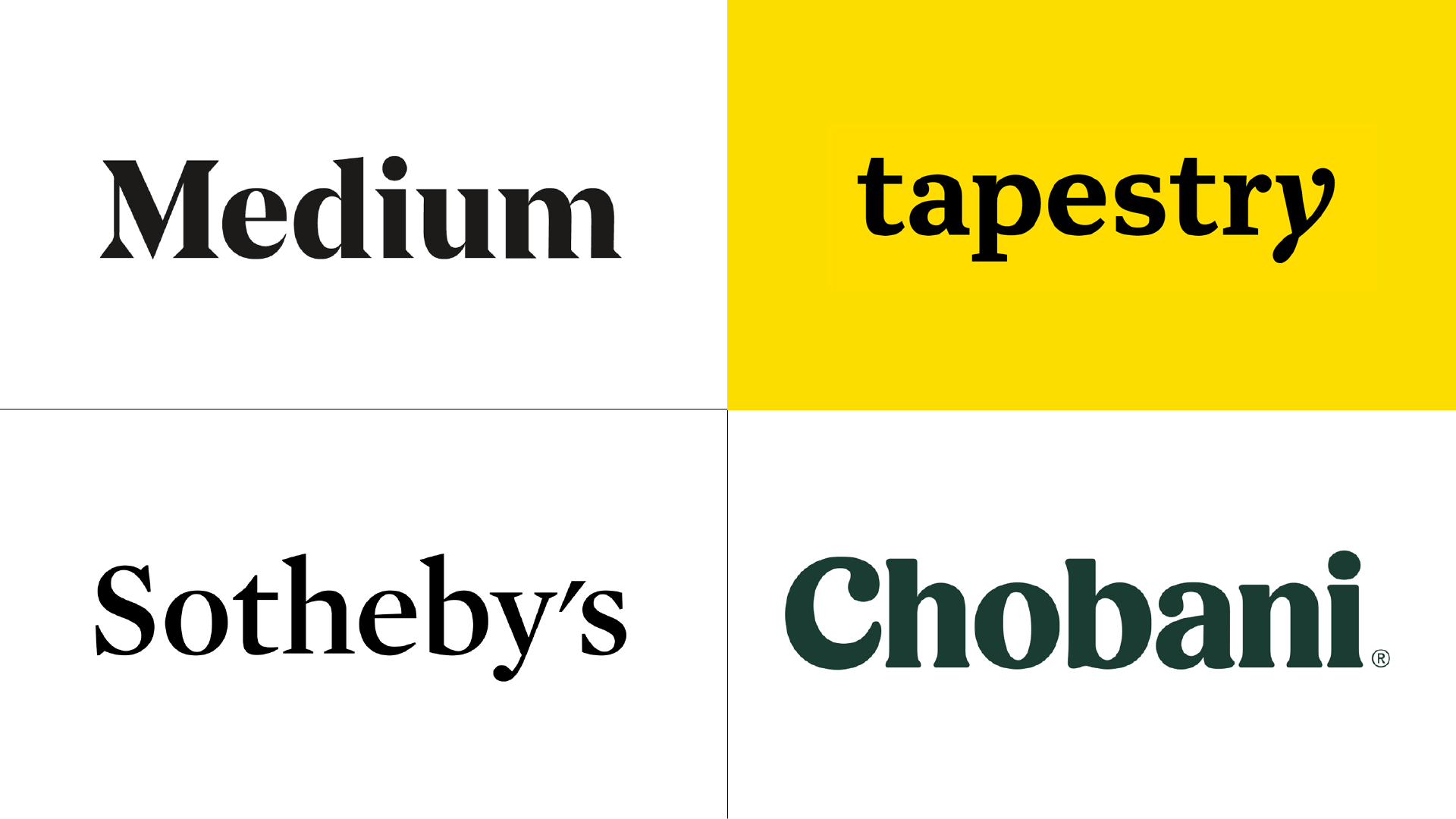
1) Medium
디자인 에이전시 Manual과 인하우스 협업
2012년에 서비스를 시작한 Medium은 미국판 Brunch라고도 불리는 대표적인 온라인 출판 플랫폼입니다. 서비스 초기에 여타 온라인 플랫폼들과 같이 모던한 산세리프체를 사용했던 Medium의 이전 아이덴티티는 다소 밋밋한 인상을 가지고 있었지만, 단단하고 개성 있는 세리프체를 활용한 리브랜딩을 통해 다른 서비스들과 비교하여 시각적으로 돋보이고 개성있다는 호평을 받았습니다
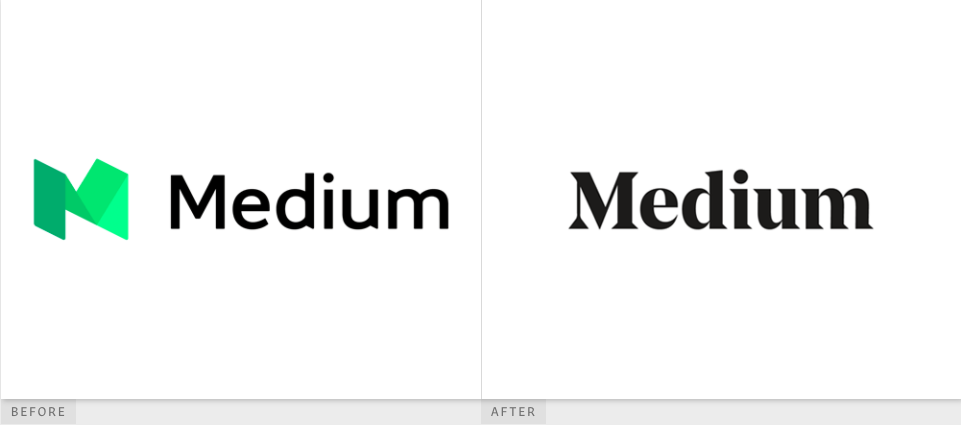
2) Tapestry
뉴욕 디자인 에이전시 Carbon Smolan Agency에서 제작
Tapestry는 Coach의 모회사로 Coach의 이름에 너무 의존하지 않기 위해 Coach Inc에서 수정된 이름입니다. Coach는 패션 브랜드 중에서 아직까지 세리프 폰트를 유지하고 있는 브랜드 중 하나인데요, 이번 Tapestry 리브랜딩에서도 공 모양의 세리프가 인상적인 서체를 사용하여 단단하면서도 부드러운 이미지의 워드마크를 제작하였습니다.
3) Sotheby’s
디자인 에이전시 Pentagram제작
Sotheby’s(소더비)는 1744년 영국, 런던에서 설립되어 고가 미술품을 취급하는 경매회사입니다. 산세리프 체인 Gill Sans체를 바탕으로 한 기존의 워드마크는 고가의 미술품을 취급하는 회사의 이미지에 비해 너무 모던하고, 신중하지 못하다는 느낌이 있었습니다.
이런 문제점을 개선하기 위해 펜타그램 뉴욕 파트너 Miller와 그의 팀은 세리프 서체인 Mercury체를 활용하여 300년이 넘는 Sotheby’s의 유산을 계승할 수 있는 아이덴티티를 선보였습니다.
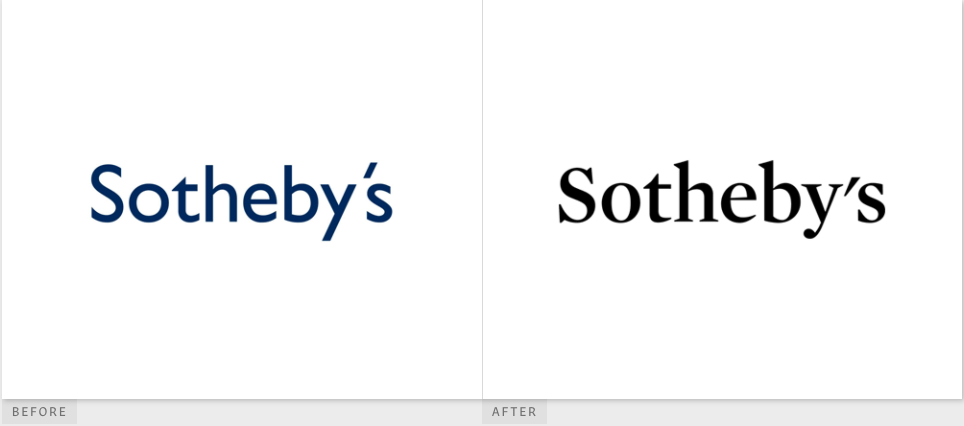
4) Chobani
인하우스 제작
2007년에 한 터키 이민자가 뉴욕의 그릭 요거트 공장을 사서 설립한 Chobani는 이제 미국에서 가장 잘 팔리는 요거트 브랜드입니다. 식품 브랜드로서는 다소 딱딱하고 개성 없는 워드마크를 사용하던 Chobani는, 2016년 디자인 에이전시 Collins의 공동 창업자인 Leland Maschmeyer의 합류와 함께 새로운 아이덴티티를 선보였습니다.
매끄럽고 두툼한 부드러운 굴곡이 특징인 새로운 워드마크는 요거트 브랜드로서의 이미지를 완벽하게 표현했다는 평을 받으며, 세리프를 활용한 리브랜딩의 대명사가 되었습니다.
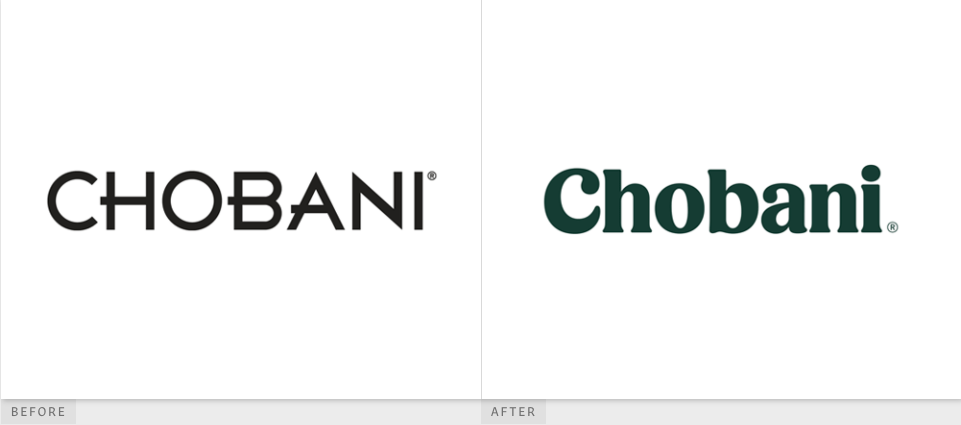
2. 커스텀 폰트 & 글자 변형
폰트로 로고를 구성하는 워드마크의 경우, 폰트의 완성도가 곧 워드마크의 완성도를 의미하기 때문에 상업적으로 큰 성공을 거둔 폰트를 사용하곤 합니다. 하지만 Helvetica와 같이 이미 너무 많은 기업들이 사용하고 있는 폰트는 오히려 해당 브랜드만의 개성을 살리기 어려울 수 있습니다.
한 브랜드만을 위해 제작된 커스텀 폰트는 타 브랜드와의 시각적인 차별성과 그 브랜드만의 고유한 성격을 만들 수 있다는 점에서 가장 좋은 해결안이 될 수도 있습니다.
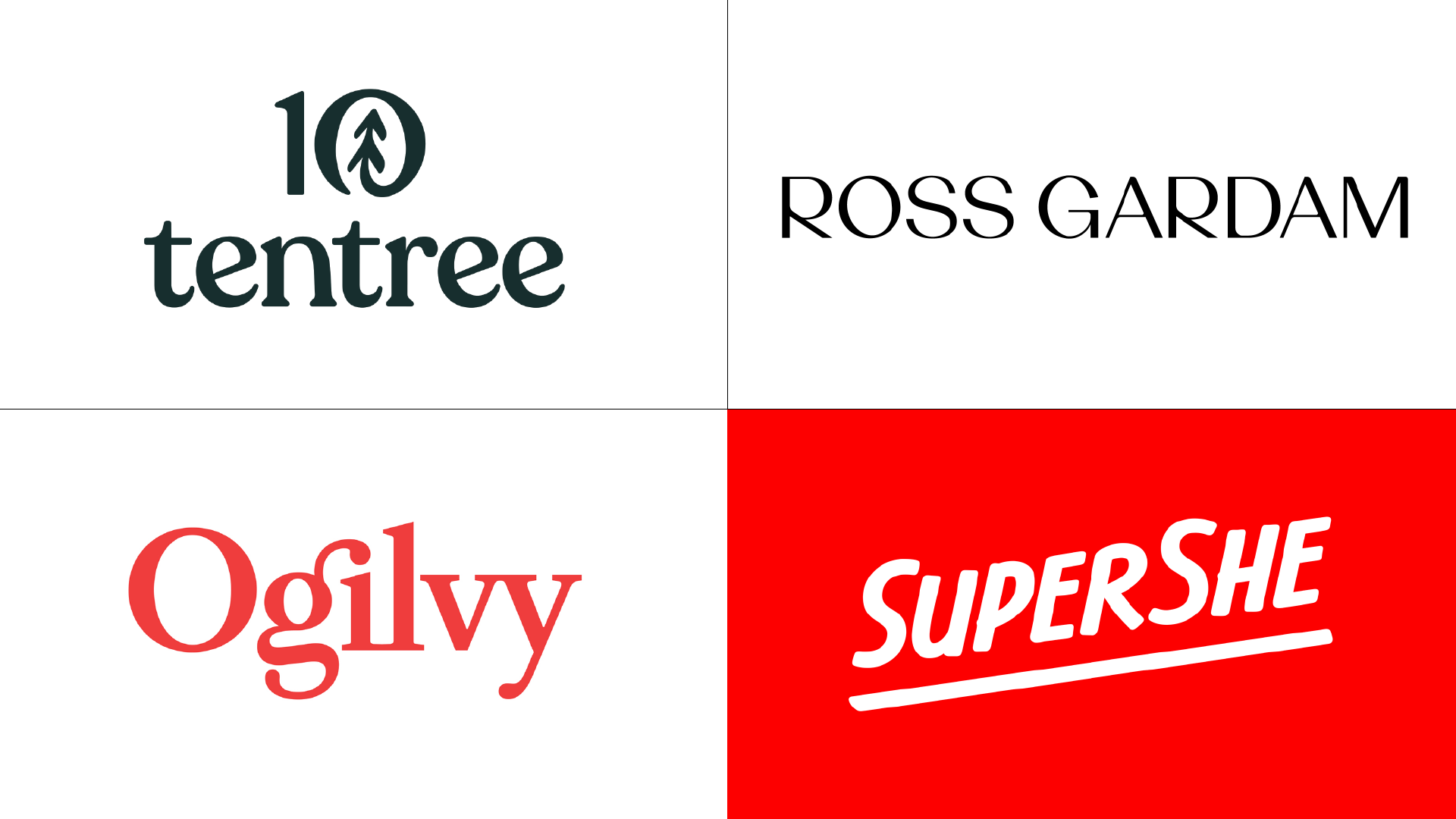
1) Tentree
디자인 에이전시 Sid Lee 와인하우스 협업
2012년에 설립된 캐나다 아웃도어 브랜드 Tentree는 브랜드의 메인 미션으로 제품을 팔기보다 나무를 심는 것을 목표로 하고 있습니다. 실제로 제품을 팔 때마다 10개의 나무를 심고 있다고 합니다. 기존의 Tentree 로고는 이런 브랜드 미션을 심벌을 통해 표현하고자 했지만, 너무 투박하고 아웃도어 브랜드로서의 인상을 전혀 주지 못한다는 문제점이 있었습니다.
Tentree는 이번 리브랜딩을 통해 아름다운 곡률과 부드러운 세리프 장식이 눈에 띄는 워드마크를 제작하여, 기존 로고 심벌의 아이디어를 계승하면서도 훌륭하게 풀어냈다는 평을 받았습니다.
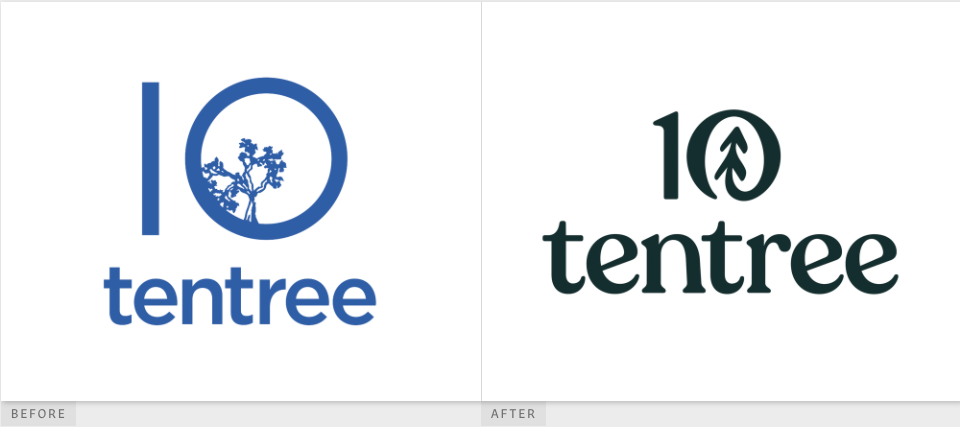
2) Ross Gardam
디자인 에이전시 SouthSouthWest 제작
Ross Gardam은 2007년 설립된 호주의 가구&조명회사입니다. 모든 제품이 지역 장인과 메이커들에 의해 수작업으로 제작되어 현대적이면서도 우아한 매력으로 인지도를 쌓고 있는 브랜드입니다.
나쁘지는 않지만 제품의 우아함을 잘 담아내지 못한다는 평이 있었던 기존의 워드마크는 이번 리브랜딩을 통해 글자 획 대비가 크고, 개성 있는 'R'이 특징인 커스텀 산세리프 서체로 수정되었으며, Ross Gardam 제품 특유의 간결하면서도 우아한 느낌을 잘 표현했다는 평을 받았습니다.
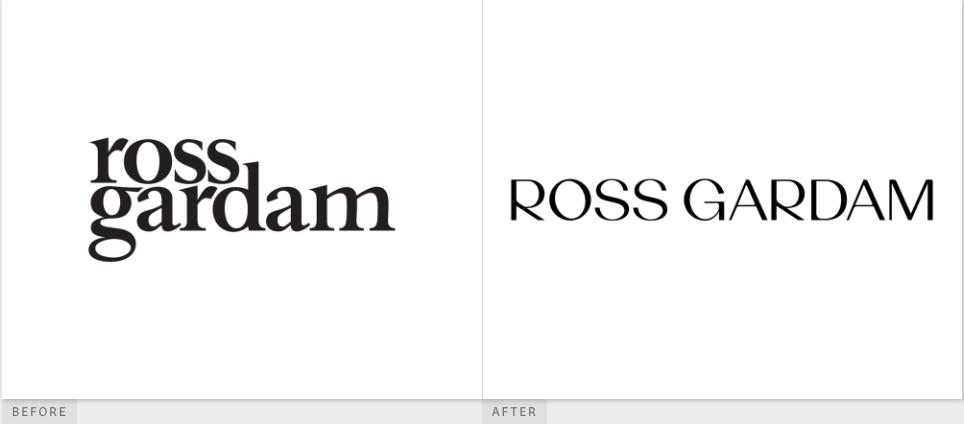
3) Ogilvy
디자인 에이전시 Collins 제작
1948년 설립된 Ogilvy는 세계에서 가장 잘 알려진 광고 에이전시 중 하나입니다. 유명 디자인 에이전시 Collins에서 제작한 이번 워드마크는 회사의 창립자 David Ogilvy의 서명과 기존 회사가 사용하던 Baskerville체를 참조하여 제작된 커스텀 워드마크입니다. 워드마크의 글자를 자세히 살펴보면 gi와 il, vy과 합쳐져 있는 형태의 합자(ligature)가 눈에 띄는데, 이는 에이전시와 클라이언트, 클라이언트와 고객들을 잇는다라는 점을 상징한다고 합니다.
이번 Ogilvy의 리브랜딩은 기존의 아이덴티티를 유지하면서도 매력적인 합자로 많은 디자이너들의 호평을 받았습니다.
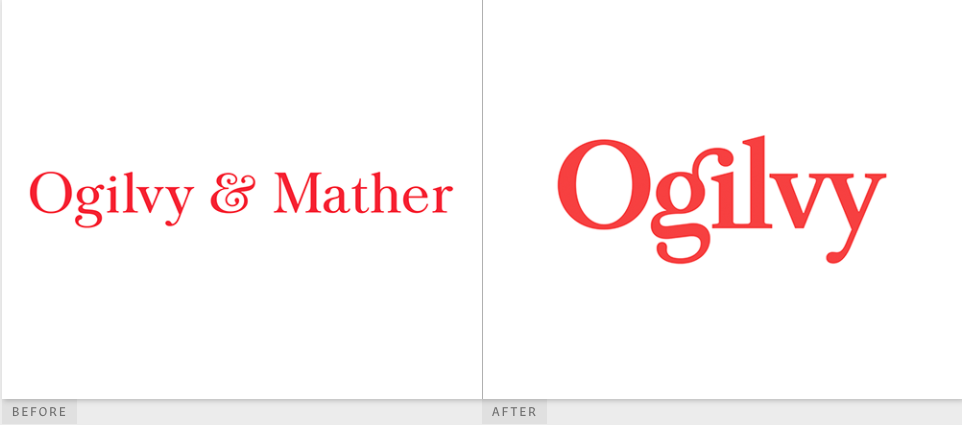
4) SuperShe
디자인 에이전시 &Walsh 제작
2018년에 설립된 SuperShe는 여성들을 위한 콘텐츠, 제품, 커넥션을 제공하는 커뮤니티입니다. 이 커뮤니티는 발틱해에 위치한 실제 섬을 기반으로 시작되었지만, 현재는 경제적인 여건으로 섬을 이용하지 못하는 여성들을 위하여 어플을 통한 커뮤니티도 운영하고 있습니다.
기존 로고의 모노그램은 파편 같은 모양으로 날카로운 인상을 풍기며 상류층 여성들을 타게팅했다면, 이번 마커로 그린 듯 한 부드러운 인상의 워드마크는 이전보다 더 폭넓은 고객층을 확보하려는 SuperShe의 브랜드 전략에 매우 적절하다는 평을 받았습니다.
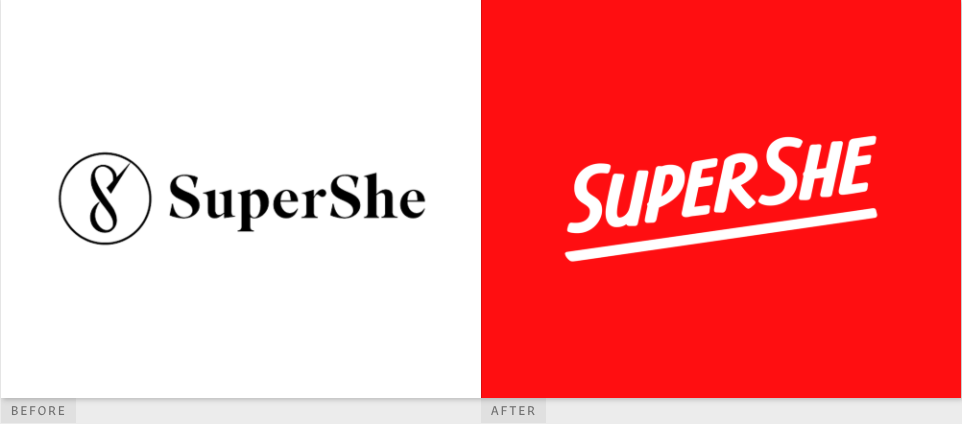
3. 다목적 용도를 위한 시각적 개선
리브랜딩은 때때로 일반인의 눈으로는 알아차리기 어려운 미묘한 변화만 거치기도 합니다. 이는 브랜드 아이덴티티의 갑작스러운 변화가 기존 브랜드의 성격 또한 변화시켜, 브랜드를 사용하는 고객이 혼란을 겪거나 거부할 수도 있기 때문이죠. 실제로 패션 브랜드 Gap이 Helvetica를 사용한 새로운 로고를 공개했다가 기존 팬층의 엄청난 반발로 다시 이전 로고로 돌아온 케이스가 있습니다.
기존 워드마크의 시각적 문제점들은 보완하는 리브랜딩은 얼핏보면 이전과 큰 변화가 없는 것 같지만, 시각적인 안정성이나 로고가 활용되는 여러 환경에서의 접근성을 높이기 위해 작은 디테일들이 수정되는 경우들이 많습니다.
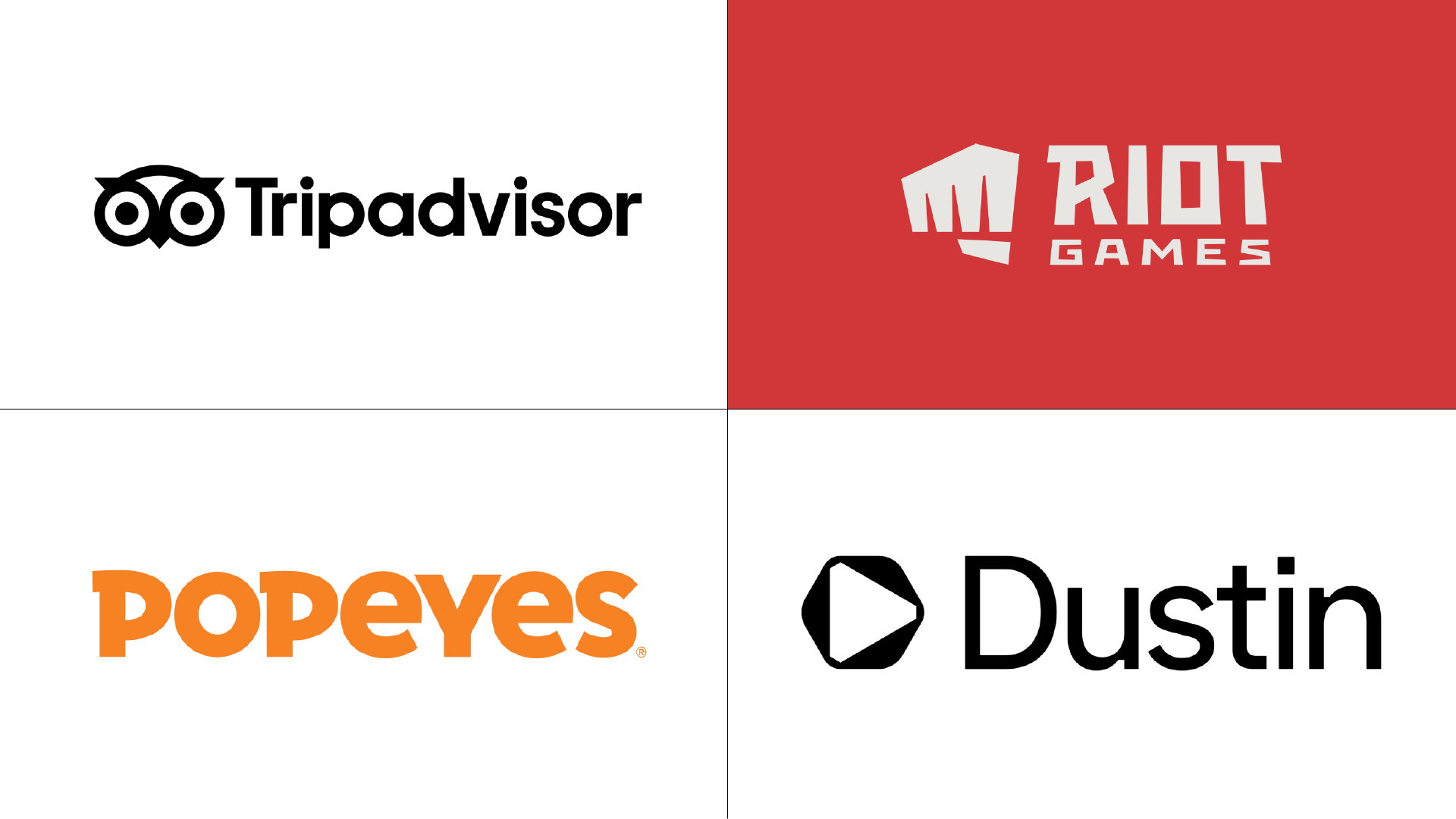
1) Tripadvisor
디자인 에이전시 Mother Design 제작
2000년에 설립된 Tripadvisor는 매월 40억 명의 여행자들의 여행 계획에 도움을 주는 세계 최대 규모의 여행 정보 플랫폼입니다. 이전의 Tripadvisor 워드마크가 불명확한 의도의 색상 사용과 default 폰트(OS 혹은 프로그램에 기본으로 탑재된 폰트)로 보이는 폰트의 사용으로 고객에게 신뢰를 주지 못하는 디자인이었다면, 이번 워드마크는 단색 심벌과 그에 어울리는 볼드한 지오메트릭 서체가 시각적으로 단단하고 안정적인 인상을 줍니다.
이번 Tripadvisor의 리브랜딩은 기존 브랜드의 아이덴티티를 유지하면서도 단색 워드마크의 활용으로 웹, 모바일, 인쇄와 같은 여러 환경에서의 접근성을 성공적으로 높였다는 평을 받았습니다.
2) Riot Games
디자인 에이전시 Rinker Design과 인하우스 협업
2006에 설립된 Riot Games는 우리에게는 LoL(League of Legends)이라는 게임으로 잘 알려진 게임회사입니다. 워드마크의 가독성이나 로고의 크기 조절이 크게 중요시되지 않던 Riot Games사의 로고는 무려 12년 동안 유지되었지만, 점차 회사가 성장하고 로고가 다양한 목적으로 활용됨에 따라 Riot Games사는 기존 로고의 문제점을 해결할 새로운 이미지가 필요했습니다.
여러 각도의 기준선으로 제작된 이번 Riot Games사의 심벌과 워드마크는 기존의 거친 매력을 그대로 유지하면서도 매우 단단하고 심플한 이미지를 구축했다는 평을 받았습니다.
3) Popeyes
디자인 에이전시 Jones Knowles Ritchie 제작
글을 마치며.
기업 및 브랜드의 리브랜딩은 단순히 많은 금액을 필요로 하기도 하지만, 기존에 유지하고 있던 브랜드의 이미지를 전면적으로 수정하는 일이기에 매우 신중하고 많은 준비를 필요로 하는 작업입니다. 이번 글에서 다룬 리브랜딩 성공 사례들이 새로운 브랜드 아이덴티티를 구축하려고 준비하시는 클라이언트 분들과 디자이너 분들에게 도움이 되었으면 합니다.